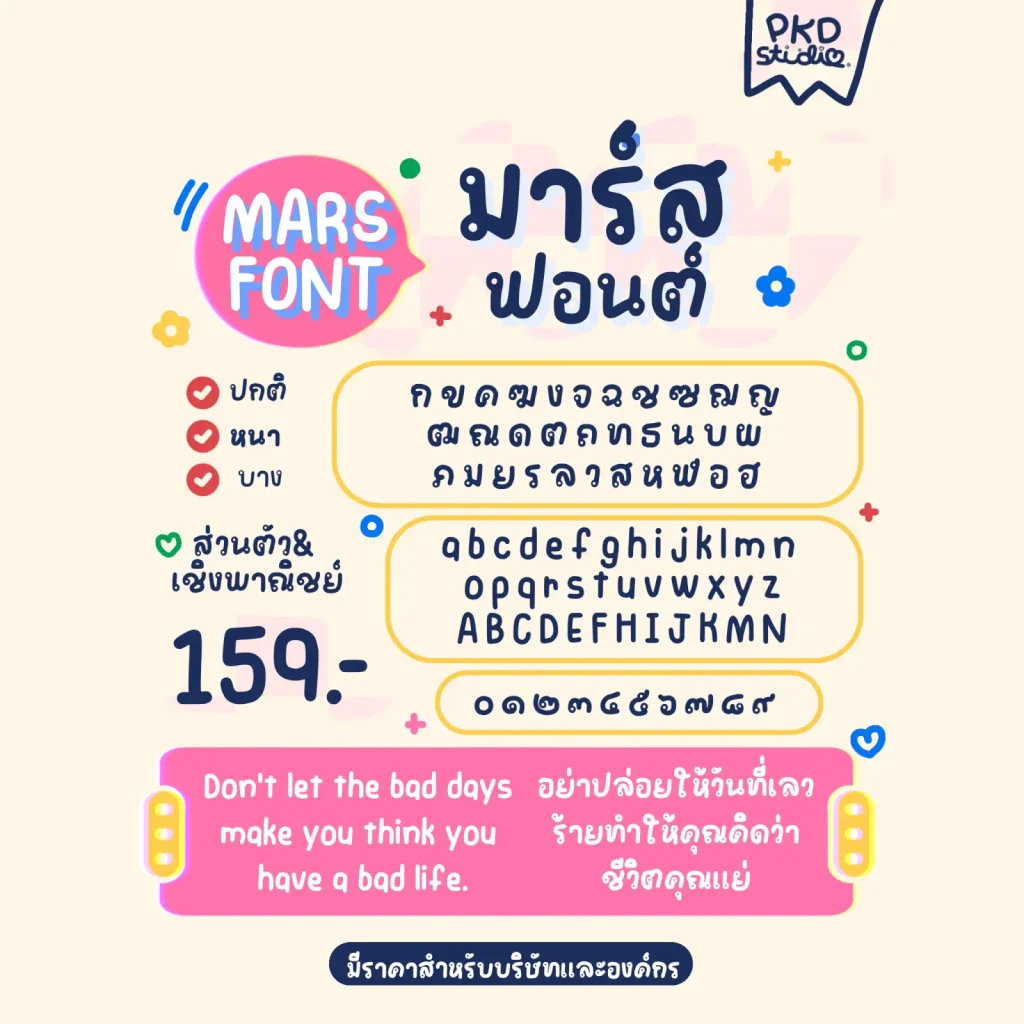
มาร์สฟอนต์ (PKD MARS) – ฟอนต์ลายมือน่ารัก สดใส เป็นกันเอง เหมาะสำหรับงานคอนเทนต์ โพสต์โซเชียล สติกเกอร์ คาเฟ่ และงานออกแบบทั่วไป
- มีตัวอักษรโปร่งผสมในบางตำแหน่ง
- ไม่มีตัวอักษรโปร่งผสม
- รองรับภาษาไทย ภาษาอังกฤษ ตัวเลข และสัญลักษณ์
มาร์สฟอนต์ (PKD MARS)